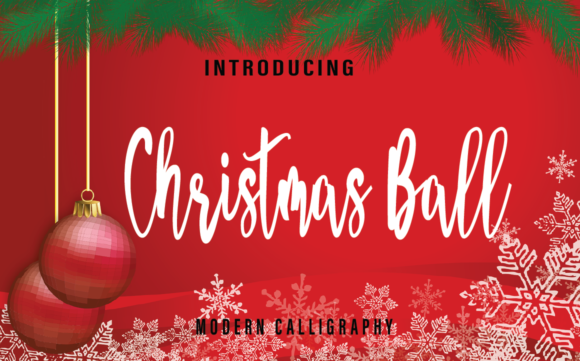
Christmas Ball - это удивительный рукописный шрифт.
Он выглядит привлекательно и естественно!
Используйте этот шрифт, чтобы вывести свои праздничные проекты на новый уровень!